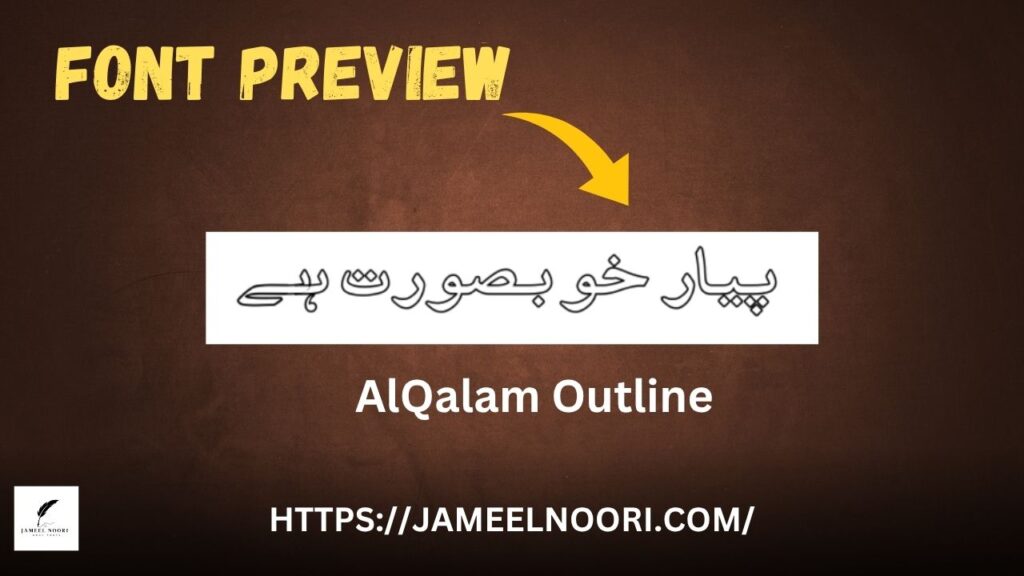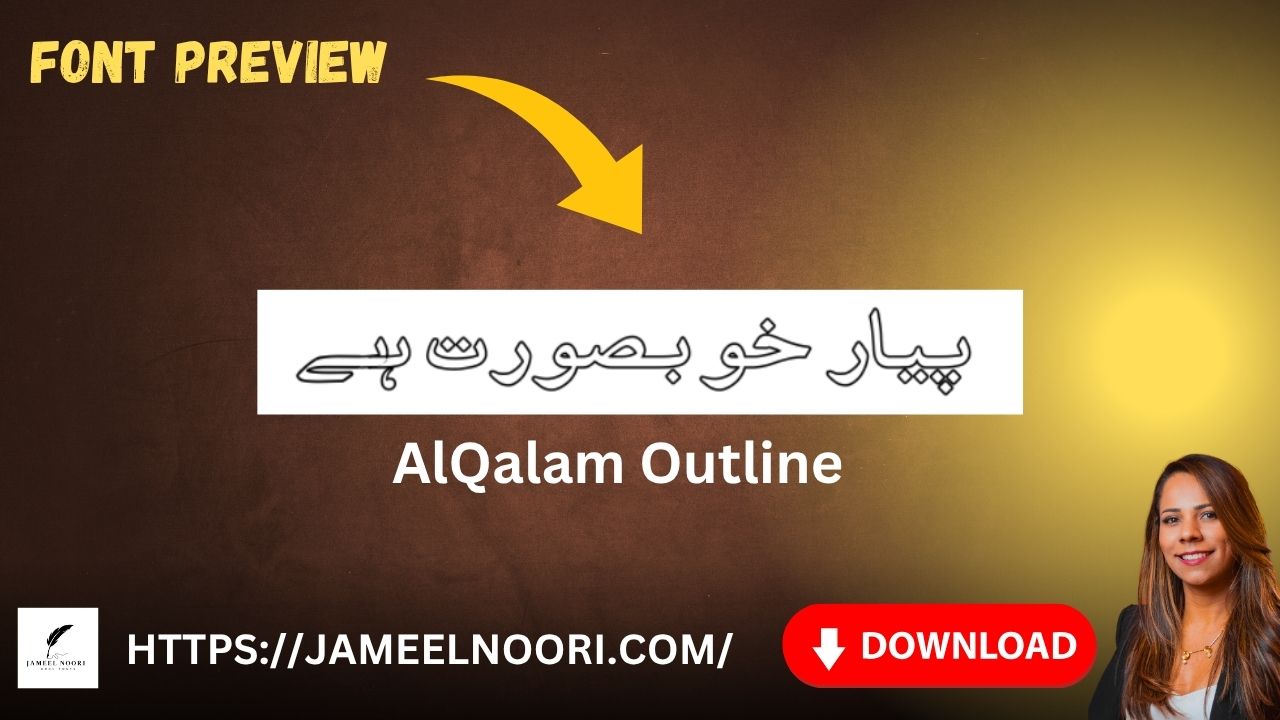
Introduction to AlQalam Outline Font
Agar aap ek unique aur stylish Urdu font ki talaash mein hain, to urdu font AlQalam Outline Font aapke liye best choice ho sakta hai. Ye font designers aur content creators ke liye specially tayar kiya gaya hai jise aap free mein download kar sakte hain jameelnoori.com se.
AlQalam Outline font ka style Outline type ka hai jo text ko ek artistic aur sharp look deta hai. Iska size sirf 66.7 KB hai aur ab tak 12,385 dafa download ho chuka hai.
Font Style | Outline |
Key Features of Urdu Font AlQalam Outline
- ✅ Stylish outline Urdu typography
- ✅ Best for headings, titles, and logo designs
Where You Can Use This Font
AlQalam Outline font ka use kai tarah se kiya ja sakta hai:
- 🔹 Urdu quotes design
- 🔹 Social media posts
- 🔹 YouTube thumbnails
- 🔹 Islamic posters
- 🔹 Invitation cards
- 🔹 Typography-based logos
Why Choose AlQalam Outline Urdu Font?
- Unique Look: Is font ka outline style Urdu fonts mein rare hai.
- Professional Output: Print aur digital dono formats mein achi readability.
6. Kya is font mein diacritical marks (zabar, zer) hain?
Nahi, ye font mainly outline style mein hai aur basic Urdu alphabets ke liye suitable hai.
9. Is font ka use thumbnail design mein hota hai?
Bilkul, isay YouTube thumbnails aur title text design ke liye use kiya ja sakta hai.